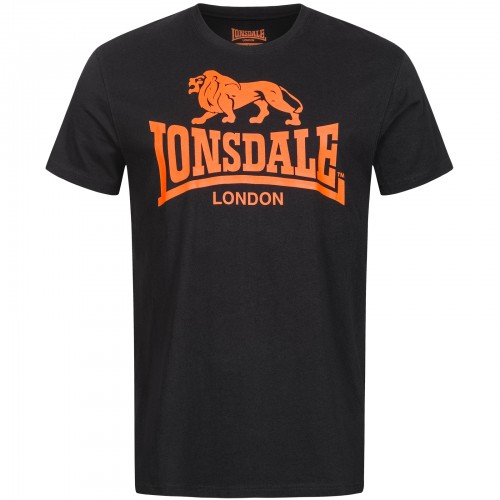
автомобили и бренды с логотипом LION
Логотип Lions Clubs International известен во всем мире как знак гуманизма и бескорыстного служения. У компании есть ряд различных логотипов, символов и значков, каждый из которых обозначает определенную программу или услугу. Большую часть времени логотип Detroit Lions представлял собой стилизованного льва. Эмблема льва впервые появилась в 1952 году, когда команда сменила название на нынешнее. Хотите узнать больше о логотипе Льва? Ниже приведена информация, которую вам необходимо знать о брендинге с логотипом Льва.
Логотип львов
«Детройт Лайонс» — профессиональная футбольная команда, выступающая в Северном дивизионе Национальной футбольной конференции. Франшиза участвует в играх НФЛ с 1930 года. В 1929 году она была основана в Портсмуте, штат Огайо. Портсмутские спартанцы были первоначальным названием команды. Он официально присоединился к Национальной футбольной лиге 12 июля 1930 года. Несмотря на то, что «Портсмутские спартанцы» добились успеха в НФЛ, Великая депрессия помешала им выжить.
Низкий доход и другие финансовые проблемы привели к тому, что владельцы франшизы продали ее группе инвесторов во главе с исполнительным директором Детройтской радиостанции Джорджем А. Ричардсом. Они заплатили 15,000 795,208 долларов за франшизу НФЛ, а также долги команды в размере 1934 XNUMX долларов. После покупки команды в XNUMX году Джордж А. Ричардс переместил ее в Детройт, штат Мичиган. По итогам своего первого сезона команда заняла второе место в Западном дивизионе.
В 1940 году Фред Мандель, руководитель чикагского универмага, заплатил за компанию 225,000 1958 долларов. Эдвин Дж. Андерсон и Лайл Файф взяли под свой контроль клуб восемь лет спустя, в 1964 году, и удерживали его до 4.5 года. Уильям Клей Форд-младший, бывший вице-президент Ford, купил контрольный пакет акций команды за 1963 миллиона долларов в Ноябрь XNUMX года, что сделало его единственным владельцем Львов.
История команды особенно интригует, потому что так мало игроков НФЛ меняли имена. Раньше они называли себя Портсмутскими спартанцами в честь своего родного города Портсмут.
Однако после переезда команды в Детройт Джордж А. Ричардс изменил название команды в честь Тигров. По словам нового владельца, отряд будет править лигой, как лев правит лесом. В 1935 году «Львы» выполнили свое обещание, выиграв свой первый чемпионат НФЛ.
История логотипа Львов
Detroit Lions и многие другие команды НФЛ имеют такое же имя, талисман и основной логотип. Первоначально он был известен как «Портсмутские спартанцы», но так было не всегда. Однако соответствующая часть названия клуба была выделена жирным шрифтом с прямоугольными засечками на логотипе клуба. Detroit Lions изменили свое название, чтобы отразить новый титул, и получили ряд символов на тему львов. Так, первый был мультяшно раскрашен, второй — белого цвета с синим контуром, а остальные — все разных цветов синего. Символ с двумя различными значениями, лев появляется на каждом логотипе Detroit Lions. В первую очередь это приветствие бейсбольной команде Detroit Tigers. Во-вторых, владельцы НФЛ хотят, чтобы деспот полностью контролировал поля лиги.
Что такое Детройт Лайонс?
Одной из известных легенд НФЛ, добившейся значительного успеха на раннем этапе, является «Детройт Лайонс», профессиональная футбольная команда, основанная в Соединенных Штатах в 1930 году. Однако «Лайонс» — единственная команда, которая не играла в Суперкубке.
История логотипа Львов 1929-1933 гг.
На логотипе было два слова, потому что «Портсмутские спартанцы» были предыдущим прозвищем команды. Слово «PORTSMOUTH» было написано заглавными буквами в верхней части логотипа, окружено черной рамкой и бежевой типографикой. Ниже появилось слово «СПАРТАНЦЫ» черного цвета с золотисто-бежевой рамкой. Заглавные буквы были использованы еще раз, но на этот раз они были немного расширены, чтобы создать идеальный прямоугольник.
История логотипа Львов 1952-1960 гг.
Естественно, лев и футболист, несущий мяч, были частью оригинального логотипа Lion. Оба проявляют честолюбие, драйв и желание действовать сразу. Зверь зарычал, открывая пасть.
Похоже, он готовился к прыжку, так как его живот был прижат к земле. Футболист ждал сигнала к атаке, одновременно запрокидывая голову вперед. Он был одет в синие джинсы, красную футболку и шлем. Обе фигуры имеют черные рамки вокруг них.
История логотипа Львов 1961-1969 гг.
В 1961 году дизайн логотипа и цветовая палитра были значительно упрощены. Базовый белый лев с бледно-голубым контуром и двумя толстыми (синими и серыми) полосами на заднем плане пригодился в новом логотипе. Цветовая гамма данного логотипа претерпела значительные изменения, перейдя в бело-голубую гамму. Живот льва все еще был крепко прижат к земле. Эта позиция продемонстрировала его сосредоточенность и готовность к излиянию силы. Дикое животное также было изображено в подтянутом и подтянутом состоянии, чтобы подчеркнуть отличное физическое состояние участников. Полноразмерный закрученный хвост льва символизирует целеустремленное внимание.
История логотипа Львов 1970-2002 гг.
Знаменитый прыгающий лев, впервые появившийся в дизайне команды в 1970 году, был ключевым компонентом логотипа той эпохи, благодаря чему его мгновенно узнавали.
Прежний логотип был полностью обновлен командой дизайнеров. Также было замечено, что животное прыгало, подняв передние лапы в воздух, а задние — на землю. Он производил динамичное впечатление своей позой. У льва не было ни глаз, ни рта, ни носа, просто грубо сделанная морда вместо лица. Фигура была окружена двумя синими и белыми контурами.